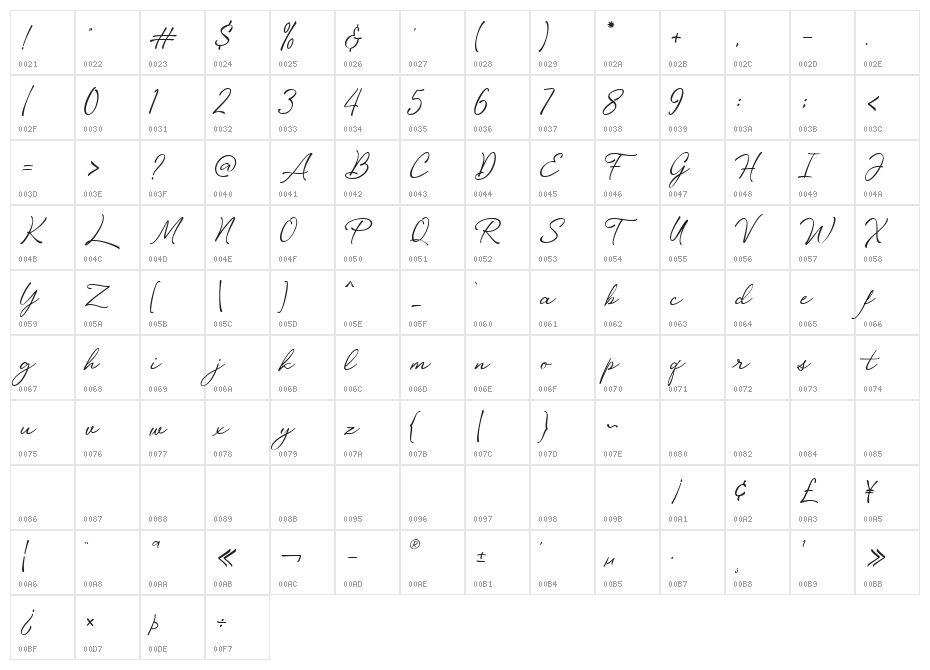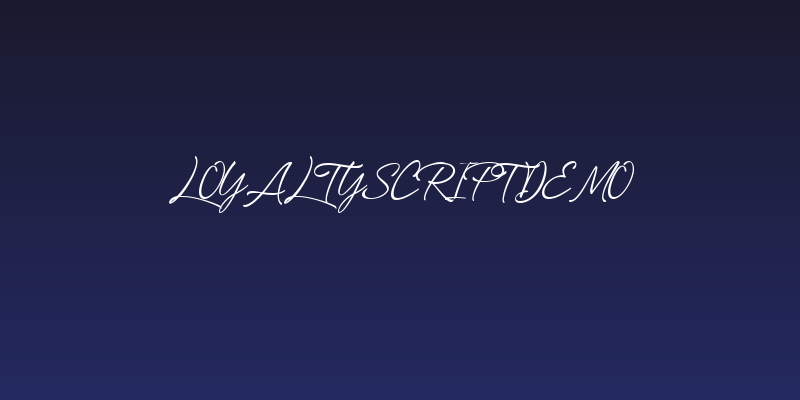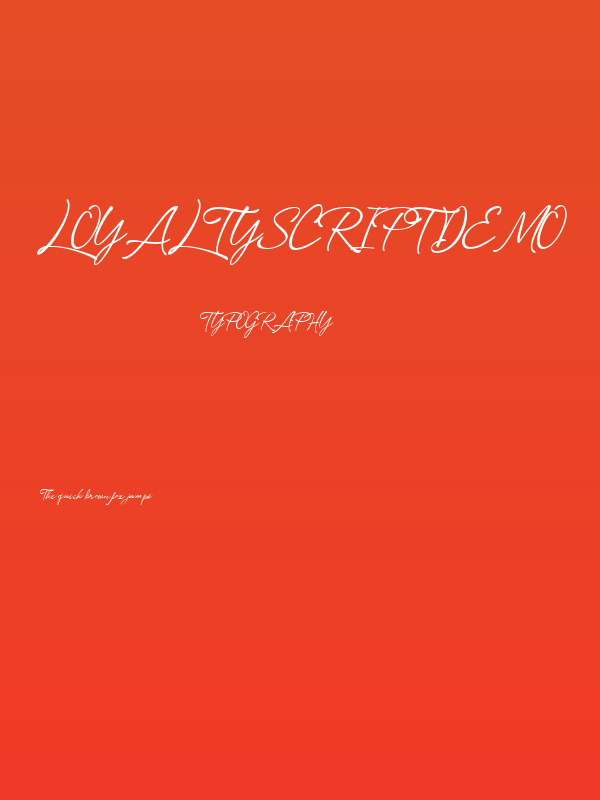
LoyaltyScriptDemo Font
| Familia fontului | Loyalty Script Demo |
| Stil general | Elegant, Sophisticated |
| Caz de utilizare | Logos, Invitations, Personal Branding |
| Proiecte propuse | Ideal for wedding invitations, greeting cards, personal branding, and elegant packaging designs. |